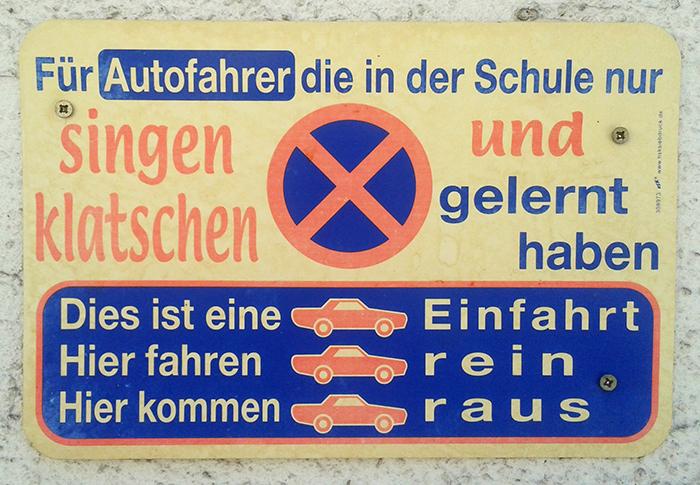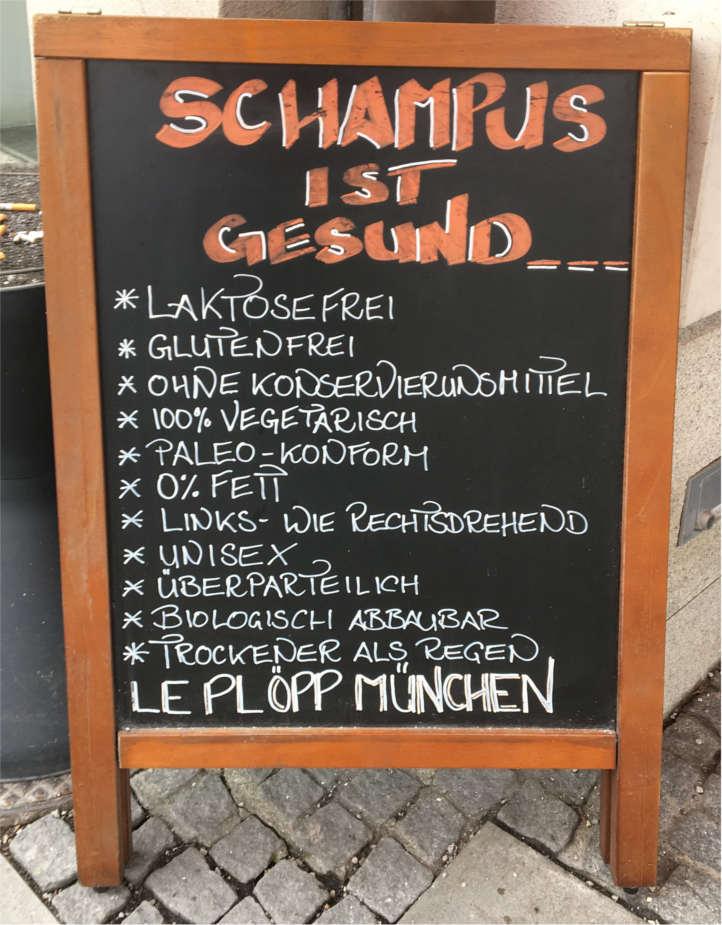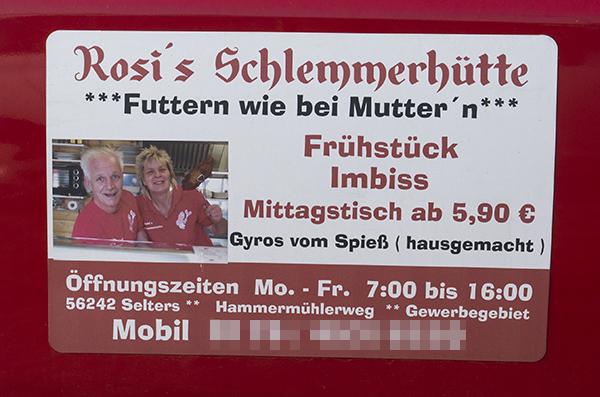
Ich weiß, ein Deppenapostroph ist keine ungewöhnliche Fundsache.  Aber hier finde ich die "Lufthäkchen" besonders nett. An Rosi’s, Susi’s, Moni’s Pommesbuden mit überflüssigen Apostrophen aus falschen Zeichen hat man sich ja längst gewöhnt. Aber "Mutter' n" ist schon eine Steigerung. Die Pommes waren lecker.
Wobei darin schon eine gewissen (wenn natürlich regelwidrige) Logik steckt. Als Auslassungszeichen zeigt der Apostroph eine Abweichung von der vollständigen formellen Schreibung an (geht es → geht’s). Bei Mutter(’)n wird zwar nichts ausgelassen, aber es ist eben auch eine informelle Schreibweise.
Da ist die (denglische) Genitivanzeige bei Rosi’s schon eine ganz andere Baustelle.
Wobei der Duden (D16, 2) diesen Apostroph vor dem Gentiv-s ja als "gelegentlich gebraucht" bezeichnet. Auch die Redaktion vom Duden ging eben ab zu in Willi’s Würstchenbude und fand das irgendwann nicht mehr schlimm – das Hingehen und den Haken vorm s.
Das mit der formellen und informellen Schreibweise habe ich so noch nicht gesehen.  Ein Apostroph als allgemeiner Anzeige einer informellen Schreibweise geht mir doch etwas zu weit. Die vielleicht darin steckende Logik war sicher nicht Antrieb, das Zeichen zu setzen. Manchmal meint man, Schildermacher müssten besonders viele Apostrophe verkaufen, weil sie schlecht werden, so wie Rosi, Willi, Susi und Hansi es  mit ihren Würstchen machen.
Ich hab noch ein Schildchen an einer Hauswand gefunden.
Ich sag ja nicht, dass ich das mit dem Mutter’n-Apostroph toll oder richtig finde. Aber so funktioniert Sprache nun mal. Existierende Konventionen werden (teilweise) missverstanden, umgedeutet, erweitert. Irgendwann ist das Falsche dann richtig. Daher würde es mich nicht wundern, wenn der Apostroph irgendwann ganz offiziell informelle Sprache und Schreibungen anzeigt.
dort hatte ich eher den Eindruck dass die Kartoffelbrei in Quader pressen und dann fritieren.
Na ja, so richtig gute Pommes sollten schon in etwa so sein, innen fast schon Püree und außen Kross.
Darum ist ja die klassische Pommes-Kartoffel im Pommesland die Bintje, eine besonders mehligkochende, und mein persönlicher Favorit hier im Mäc-Pom die DDR-Züchtung  Adretta, in gut 1cm dick Stifte geschnitten, in frischem Öl bei rel niedriger Temperatur so lange vor-frittieret, bis die Stäbchen deutlich singen, dann nach Abkühlen bei höherer Temperatur außen schon knusprig, echt suuuper lecker.
Heute in München, nahe Viktualienmarkt:
Bleibt die Frage: Welche Schrift wurde verwendet? Und gibt es die auch kostenfrei, laktosefrei, vegetarisch, glutenfrei? :party:
… und wer erzählt Le Plöpp mal wie Schatten funktionieren :-?